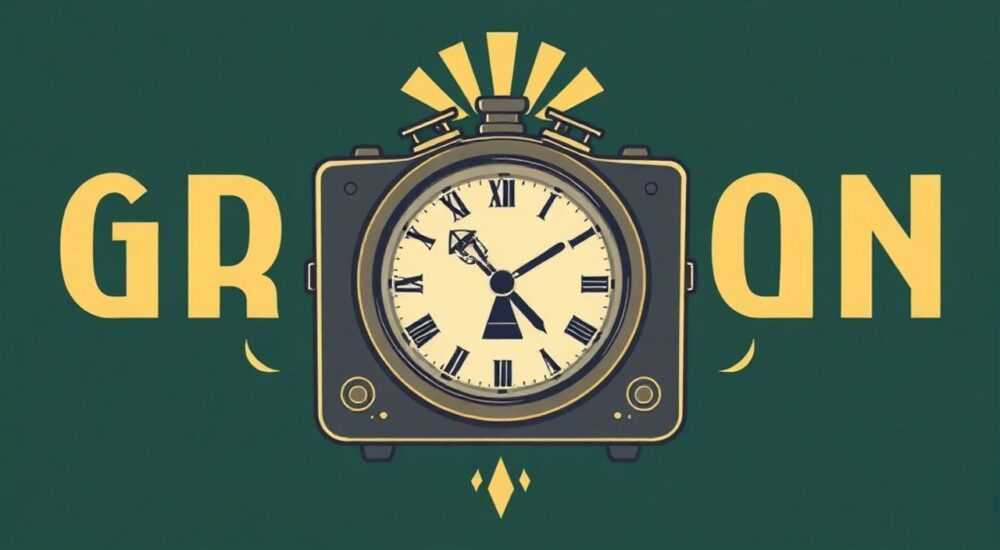
Шрифт в стиле ар деко
Шрифты в стиле ар-деко — это мощный инструмент визуальной идентичности, сочетающий роскошь, геометрию и элегантность 1920–1930-х годов. Они активно используются в брендинге, упаковке, моде и дизайне интерьеров, где требуется передать шик, динамику и историческую глубину. Выбор правильного шрифта в этом стиле требует понимания его ключевых характеристик: симметрия, вертикальная ориентация, декоративные завершения, контрастные линии и отсылки к архитектуре и искусству того времени.
Характеристики шрифт в стиле ар-деко
Ар-деко (от франц. *Arts Décoratifs*) зародился в 1920-х годах как реакция на модерн и ар-нуво. Этот стиль стремился к рациональности, но при этом не отказывался от декора. Шрифты ар-деко отражают дух машинной эпохи, сочетая геометрию, симметрию и намёк на экзотику — от египетских мотивов до авангарда.
Ключевые черты таких шрифтов:
- Выраженная вертикальная ориентация — буквы тянутся вверх, создавая ощущение величия и динамики.
- Геометрическая основа — использование кругов, треугольников, ромбов и других фигур в построении букв.
- Контраст между толстыми и тонкими штрихами — особенно заметно в засечках и соединениях.
- Декоративные окончания — стрелы, пики, радиальные лучи, напоминающие солнце или решётки лифтов.
- Симметрия и ритм — каждая буква словно часть архитектурного ансамбля.
Отличие от других стилей
Не стоит путать ар-деко с ар-нуво или Баухаусом. Ар-нуво более органичен, с плавными линиями и растительными мотивами. Баухаус, напротив, минималистичен и функционален. Ар-деко — это компромисс: он механистичен, но украшен. Он формален, но театрален.
Например, в шрифте Broadway чётко прослеживается влияние ар-деко: вертикальные вытянутые формы, массивные засечки, напоминающие колонны. В то время как Futura — чистый Баухаус, без лишних деталей.
Популярные шрифты ар-деко: обзор и применение
Ряд шрифтов стали классикой жанра. Они доступны в цифровом виде и активно используются в графическом дизайне.
Шрифт |
Год создания |
Область применения |
Broadway |
1927 |
Массивные засечки, вертикальная динамика, сильная симметрия |
Логотипы, театральные афиши, премиальная упаковка |
Art Deco |
1925 (вдохновлён выставкой) |
Утончённые линии, радиальные лучи, египетские мотивы |
Бренды роскоши, ювелирные изделия, парфюмерия |
Zapfino (частично) |
1998 |
Хотя создан позже, содержит декоративные элементы ар-деко |
Свадебная полиграфия, VIP-приглашения |
Nile |
1930-е |
Египетские мотивы, клиновидные окончания, вертикальность |
Исторические проекты, кино, музеи |
Как использовать шрифты ар-деко в современном дизайне
Стиль ар-деко не устаревает — он трансформируется. Сегодня его можно встретить в логотипах косметических брендов, интерьерах ресторанов, коллекциях одежды и даже в мобильных приложениях премиум-класса.
Правила применения
- Используйте только для заголовков и акцентов. Текстовые блоки в таком шрифте трудночитаемы.
- Комбинируйте с нейтральными шрифтами. Например, заголовок — Broadway, основной текст — Helvetica Neue.
- Соблюдайте цветовую палитру. Золото, чёрный, белый, бордовый, изумрудный — классика ар-деко.
- Добавьте текстуры. Мрамор, латунь, дерево — усиливают эффект.
Примеры успешного использования
- Coco Chanel — многие рекламные кампании используют шрифты с ар-деко элементами, отсылая к 1920-м годам.
- The Great Gatsby (2013) — в титрах и оформлении фильма доминируют ар-деко шрифты и мотивы.
- Louis Vuitton — сезонные коллекции часто включают узоры и шрифты, вдохновлённые этим стилем.
Представьте, что вы создаёте логотип для нового бренда элитного текила. Вы выбираете шрифт с вертикальными линиями, напоминающими агаву, и добавляете золотистые вставки. Это создаёт ощущение роскоши и истории — именно то, что нужно.
Типичные ошибки и как их избежать
Даже опытные дизайнеры допускают просчёты при работе с ар-деко шрифтами.
Перегрузка деталями
Часто дизайнеры комбинируют слишком много декоративных элементов: золото + узоры + тень + градиент. Результат — визуальный хаос.